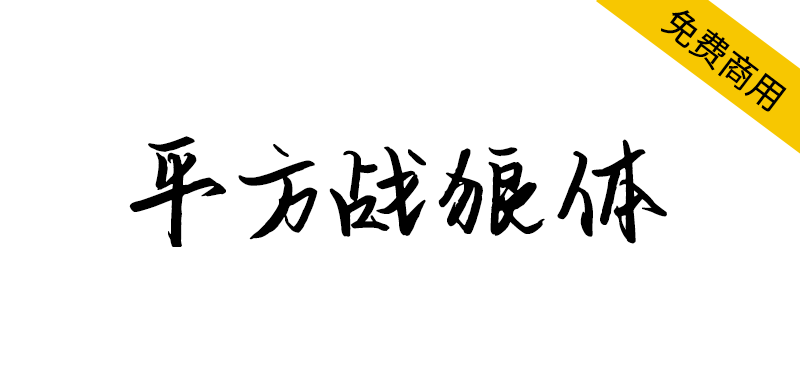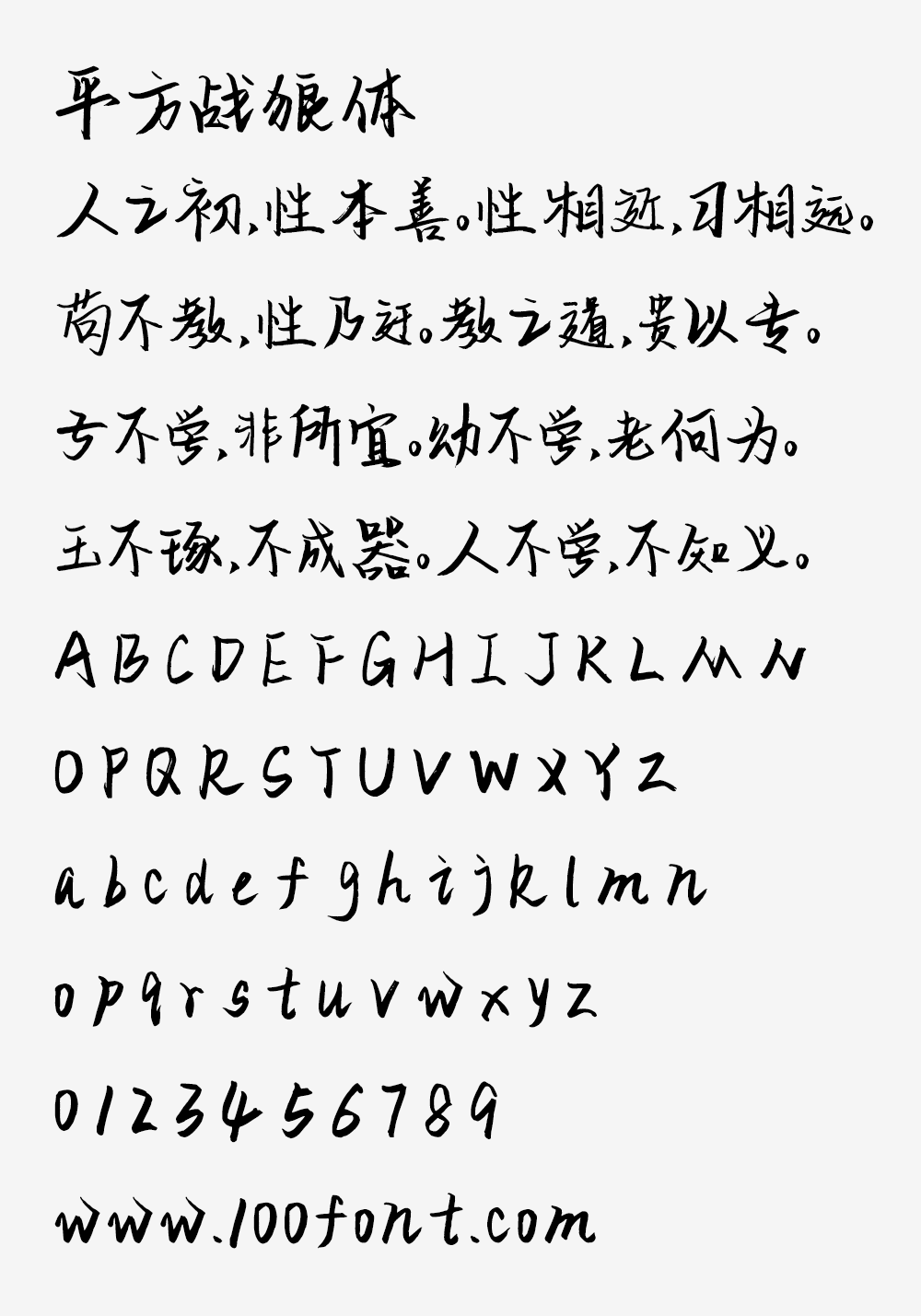
【平方战狼体】一款苍劲有力的硬笔书法手写字体
还在为设计作品缺少视觉冲击力而烦恼?这款「平方战狼体」用硬笔书法的刚劲笔触打破常规字体局限!每道笔画都带着手写特有的力度与连贯感,让文字瞬间充满张力。最惊喜的是——完全免费商用!从广告海报到电商 Banner,从自媒体配图到品牌包装,都能即刻提升设计质感。立即体验这款能让你从千篇一律的模板中脱颖而出的利器!
【平方战狼体】一款苍劲有力的硬笔书法手写字体
平方战狼体是一款展现硬笔书法特色的手写字体,其线条刚劲挺拔,笔势连贯流畅,完美呈现硬笔书写的力度感,该字体适合用于各类文案排版与设计场景。